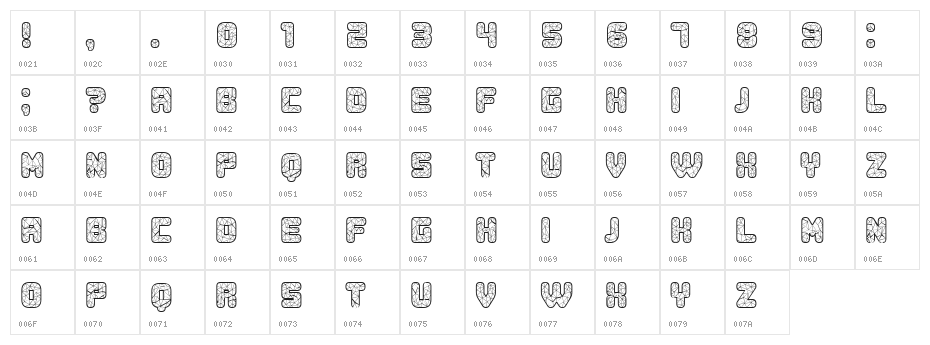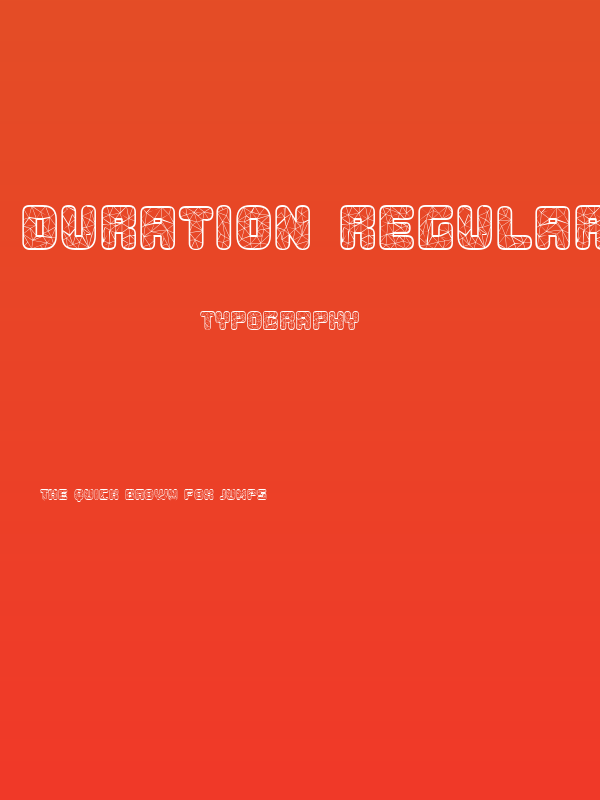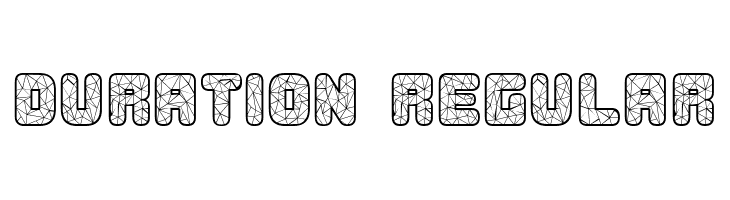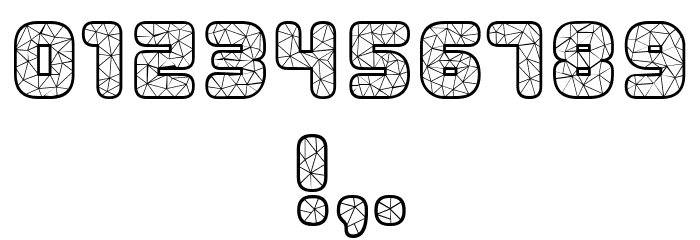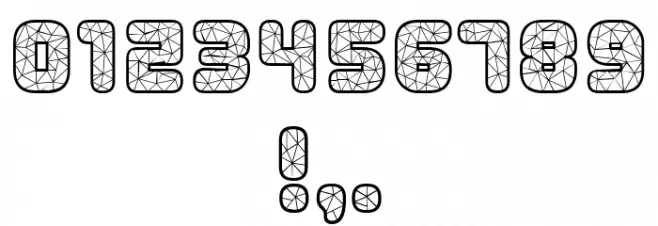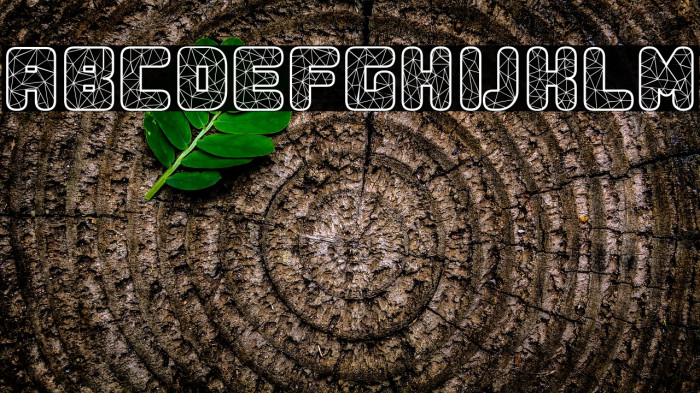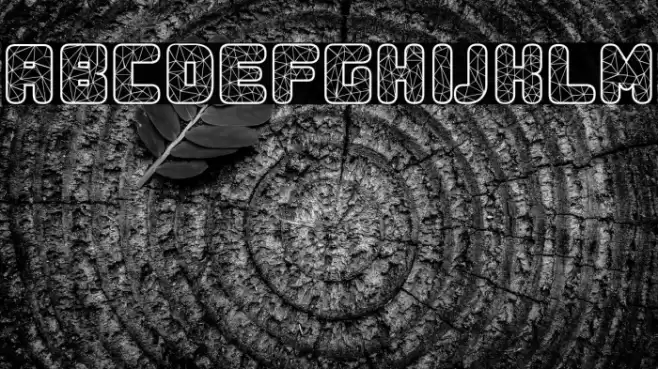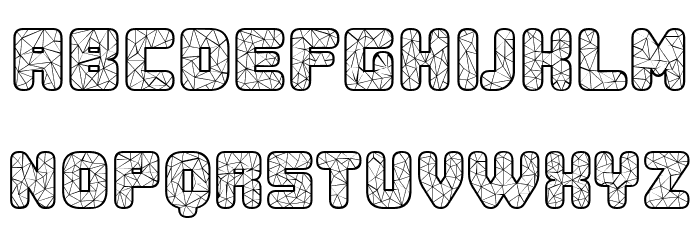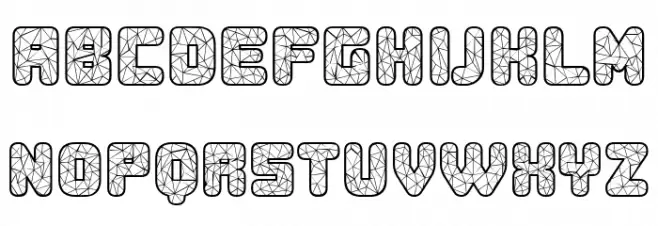
Duration Regular Font
| Anwendungsfall | Logos, Headlines, Posters |
| Vorgeschlagene Projekte | Ideal for futuristic designs, tech-related branding, posters, and digital art projects. |